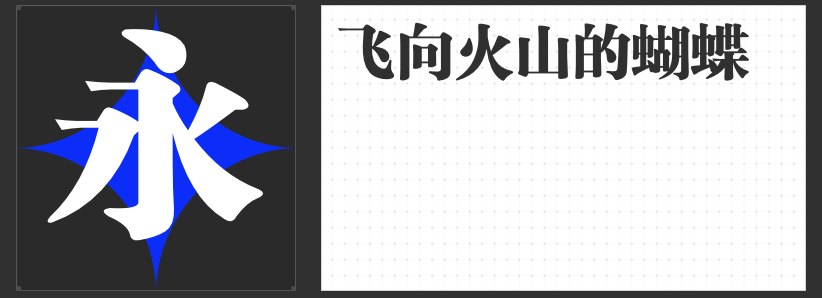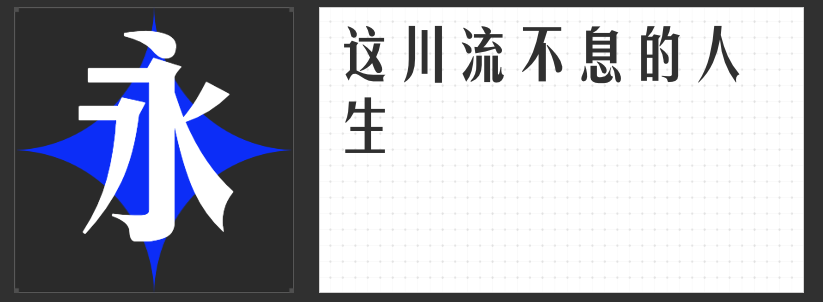
四款全能型设计字体推荐:重塑视觉表达的多元美学
在当代设计语境中,字体的选择直接影响信息传递的效率与情感温度。本文精选四款风格各异的商业字体,从现代几何到传统再造,从极简主义到装饰性表达,为设计师提供覆盖多元场景的解决方案。
一、高手庆科竞速体 常规
这款以“速度感”为核心理念的字体,通过瘦长工整的字形与均匀布白构建出理性秩序。直线设计消解了传统字体的曲线柔感,横竖笔画等粗处理强化了视觉稳定性,而“去钩化”的笔画末端斜切处理,既保留了工业设计的利落感,又通过内部留白的精准调控避免了机械字的冰冷。
二、励字美黑简
作为黑体与宋体的融合实验,这款字体以匀称的骨架平衡了黑体的现代感与宋体的书卷气。方头方尾的笔画末端通过微弧过渡软化了锐利感,中宫适度收紧的布局让小字号阅读依然清晰,而横竖笔画的适度粗细对比则赋予文字节奏感。其端正而不失灵动的气质,使其成为政府公告、教育出版等需要权威性与亲和力并存的场景的理想选择。
三、励字魔方黑简
以“魔方”为概念设计的这款字体,通过极致的几何化处理将文字转化为视觉符号。完全等宽的笔画与90度转折构建出建筑般的稳固感,粗细对比强烈的横竖线条形成视觉焦点,适合作为海报标题或品牌标识的核心元素。其无衬线设计消解了文化属性,使字体具备跨语言、跨媒介的普适性,尤其适配极简主义或未来风格的设计语言。
四、励字新粗宋简
这款字体在保留宋体横细竖粗、字脚装饰等经典特征的基础上,通过扁方字型与尖端笔画的创新,打破了传统宋体的程式化印象。适度夸张的衬线设计强化了文字的装饰性,而打破常规的结体方式则赋予字体现代活力。其古典与前卫并存的特质,既能承载文化类项目的厚重感,也可为时尚品牌注入东方美学基因。
这四款字体通过不同的设计策略,展现了文字从功能载体到美学符号的转化可能,为设计师提供了突破常规的视觉语言工具箱。